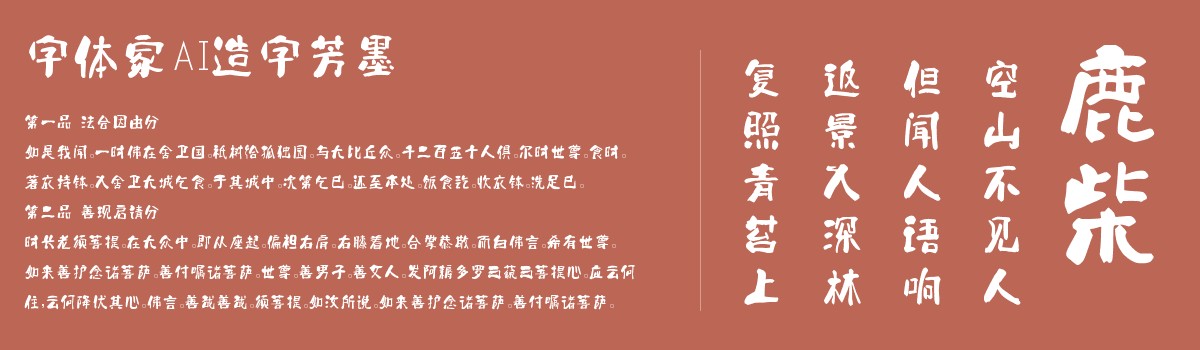
字体家AI造字芳墨
字体家AI造字芳墨是一款由字体家AI神笔造字生成的艺术字体,这款字体带有传统手写书法的韵味,笔画有自然的粗细过渡:起笔处似有轻微顿挫的厚实感,收笔偶带轻盈舒展;转折多呈圆润弧度,无生硬棱角。整体结构端庄稳重,各部分穿插避让自然,兼具典雅底蕴与灵动气息。边缘肌理似毛笔划过纸张的细微起伏,触感厚实处沉稳、轻盈处飘逸,粗处如厚布般扎实,细处似丝线般柔韧,转折圆润如鹅卵石般温润。适合用于一些广告标题、平面文案、海报标题、网页广告用字的编辑。